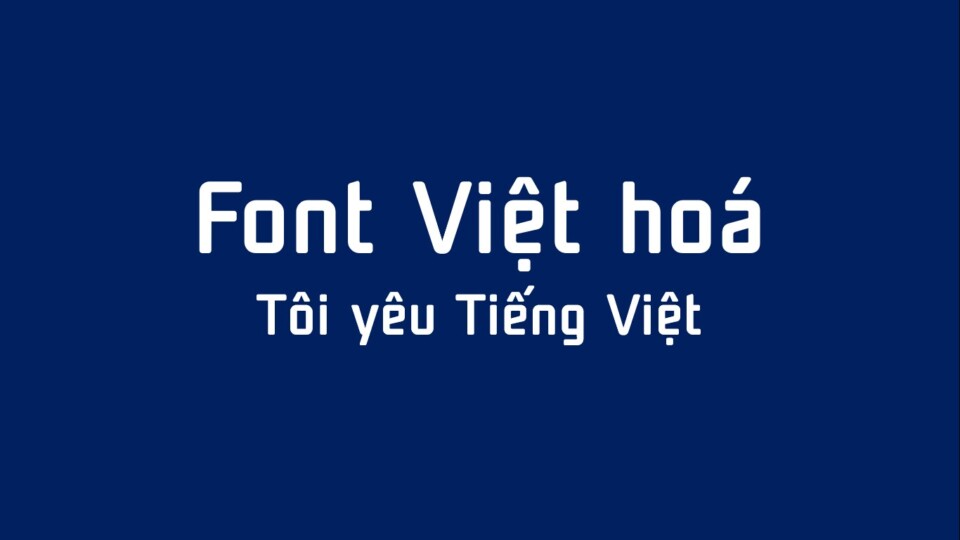
Font Việt hoá Unicod
Khám phá bộ sưu tập Font Việt hoá Unicod đẹp nhất cho thiết kế trường học
Tìm hiểu về dòng Font Việt hoá Unicod phổ biến
Trong kỷ nguyên số hiện nay, việc lựa chọn Font Miễn Phí phù hợp đóng vai trò quan trọng trong việc truyền tải thông điệp giáo dục. Font Việt hoá Unicod là những bộ chữ được tinh chỉnh để hỗ trợ hoàn hảo bảng mã tiếng Việt chuẩn quốc tế, giúp người dùng không còn lo lắng về lỗi hiển thị ký tự. Đối với các bạn học sinh và thầy cô giáo, việc sử dụng các font chữ này giúp bài giảng, báo cáo và dự án sáng tạo trở nên chuyên nghiệp và thẩm mỹ hơn rất nhiều.
Ưu điểm nổi bật của bộ chữ Unicod
Đặc điểm lớn nhất của bộ Font Việt hoá Unicod chính là sự tương thích đa nền tảng. Dù bạn đang sử dụng phần mềm soạn thảo văn bản đơn giản hay các ứng dụng thiết kế đồ họa phức tạp, những font chữ này luôn đảm bảo sự ổn định. Ngoài ra, phong cách thiết kế của chúng rất đa dạng, từ những nét thanh mảnh, hiện đại cho đến những kiểu chữ thư pháp đậm chất nghệ thuật, đáp ứng mọi nhu cầu từ làm Slide thuyết trình đến trang trí bảng tin lớp học.
Cách ứng dụng Font Việt hoá Unicod hiệu quả trong học tập
Để tối ưu hóa hiệu quả thị giác, người dùng nên kết hợp các kiểu chữ khác nhau một cách khéo léo. Chẳng hạn, bạn có thể chọn một font chữ đậm, không chân để làm tiêu đề nổi bật, sau đó sử dụng các font có chân truyền thống cho phần nội dung chi tiết để tạo cảm giác dễ đọc. Việc nắm vững cách sử dụng Font Việt hoá Unicod không chỉ giúp sản phẩm của bạn trông bắt mắt mà còn thể hiện sự chỉn chu, tôn trọng người xem trong môi trường học đường.